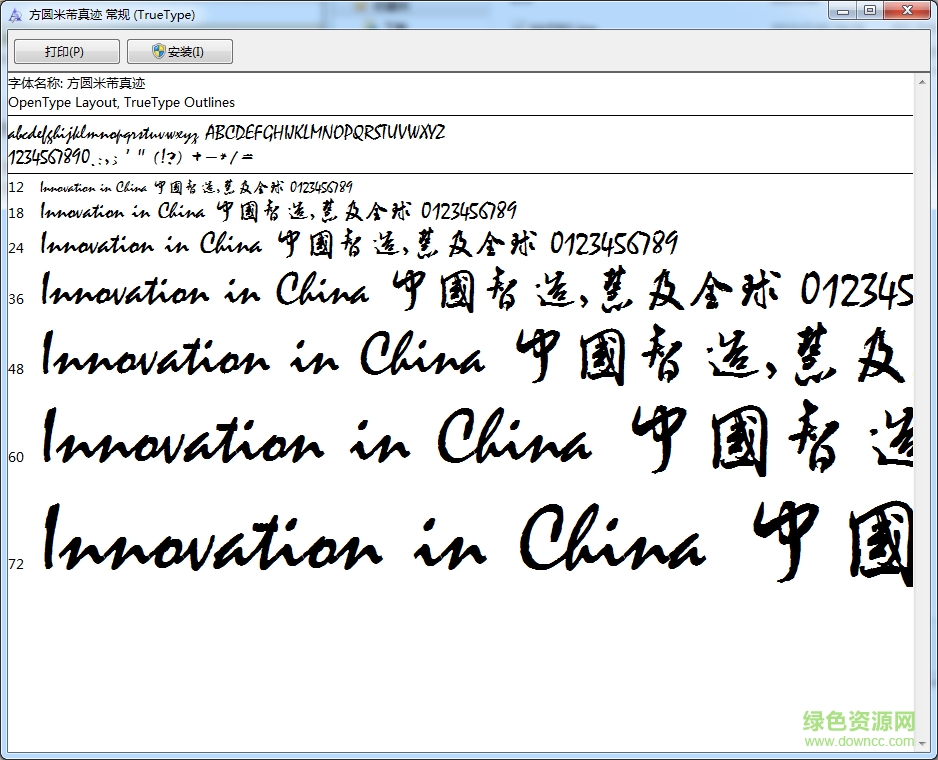
方圓米芾真跡
方圓米芾真跡是一款涉及領域廣泛的電腦字體,字體大方端正彰顯個性,適用于電腦各系統(tǒng),一鍵安裝便可使用??靵砭G色資源網(wǎng)下載體驗吧!
方圓米芾真跡字體介紹
方圓米芾真跡字體是中文字體庫中的一款字體,方圓米芾真跡字體是一款用于書法設計方面的字體,喜歡或需要此字體的朋友們可以前來下載使用。